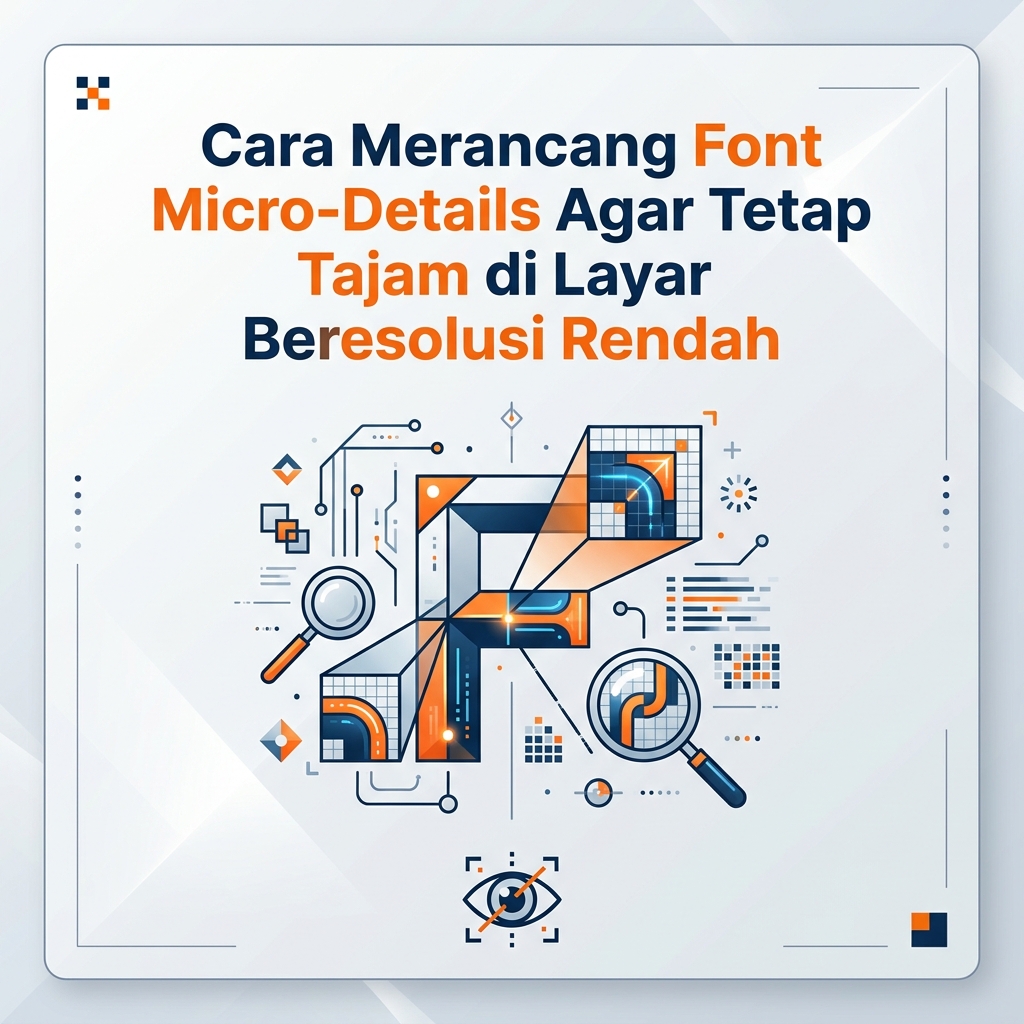
Cara Merancang Font Micro-Details Agar Tetap Tajam di Layar
Gubuku – Pernah nggak sih, lagi asyik scrolling web atau aplikasi di HP, terus nemu teks yang kelihatan buram, peyot, atau malah ‘gepeng’ nggak jelas? Bikin mata pegel dan pengen langsung close tab, kan?
Di era visual modern sekarang, micro-details pada typography bukan sekadar urusan estetika, tapi penentu utama kenyamanan membaca (readability). Masalahnya, nggak semua user pakai layar OLED flagship retina display terbaru. Banyak dari mereka yang masih akses konten kamu dari layar beresolusi rendah (low-PPI).
Kalau font kamu struggle di layar biasa, engagement platform kamu bisa langsung drop! Biar desain kamu tetap aesthetic dan crisp di segala device, simak rahasia merancang font micro-details berikut ini.
1. Sederhanakan Serif dan Eliminasi Garis Tipis (Hairlines)
Layar beresolusi rendah bekerja berdasarkan grid piksel yang terbatas. Garis yang terlalu tipis (hairlines) atau ekstrimnya lekukan serif yang rumit sering kali “hilang” atau terpotong karena piksel layar tidak cukup rapat untuk menyusun garis tersebut.
• Solusi: Pilih atau rancang stroke yang lebih tebal dan konsisten. Kalau kamu merancang font Sans-Serif, pastikan terminal (ujung garis) berbentuk tegas. Jika memakai Serif, gunakan tipe Slab Serif yang bentuk kakinya lebih tebal dan rata.
2. Memperbesar X-Height (Tinggi Huruf Kecil)
X-height adalah proporsi tinggi huruf kecil (seperti x, a, e, o) dibandingkan dengan huruf kapital. Font dengan x-height yang terlalu rendah bakal terlihat mungil dan tenggelam saat di-scale down di layar low-res.
• Solusi: Naikkkan rasio x-height. Huruf kecil yang lebih jangkung memberikan ruang dalam (counter) yang lebih lega, sehingga huruf seperti “e” atau “a” tidak akan memblok jadi bintik hitam yang samar.
3. Beri Ruang Napas dengan Aperture Terbuka
Aperture adalah ruang terbuka pada huruf-huruf seperti c, e, s, dan a. Pada layar buram/piksel kecil, aperture yang terlalu sempit bakal bikin huruf e kelihatan seperti huruf o, atau huruf c disangka huruf o.
• Solusi: Buat bukaan (aperture) lebih lebar. Ini menjaga identitas visual tiap karakter tetap jelas walau piksel layar saling menumpuk.
4. Buka Tracking & Letter-Spacing
Kerning dan tracking yang terlalu rapat (tight) adalah musuh utama layar beresolusi rendah. Efek blur dari piksel akan membuat huruf-huruf saling menempel (bleeding).
• Solusi: Longgarkan sedikit letter-spacing (jarak antar huruf), terutama untuk teks berukuran kecil (body text di bawah 14px). Jarak ekstra memberi toleransi pada piksel untuk merender tiap tepi karakter.
5. Maksimalkan Font Hinting
Ini dia senjata rahasia para desainer tipe profesional: Font Hinting. Hinting adalah proses menyisipkan instruksi matematika ke dalam file font agar garis vector huruf secara otomatis “paspas-an” menyesuaikan grid piksel layar.
• Solusi: Gunakan software pembuat font (seperti Glyphs, FontLab, atau Robofont) untuk mengatur autohinting atau melakukan manual hinting pada ukuran teks terpenting.
Cheat Sheet Ringkas Merancang Font Anti-Buram
Elemen Font Layar Beresolusi Tinggi (Retina) Layar Beresolusi Rendah (Low-Res)
X-Height Bebas / Variatif Wajib Lebih Tinggi
Aperture Bebas / Eksperimental Terbuka Lebar
Contrast Stroke Kontras Tinggi OK (Garis sangat tipis) Kontras Rendah/Sedang (Garis tebal rata)
Spacing Standar / Rapat Agak Longgar (Generous)